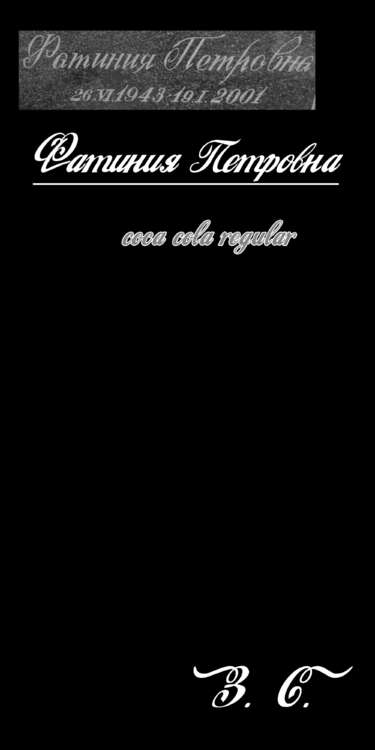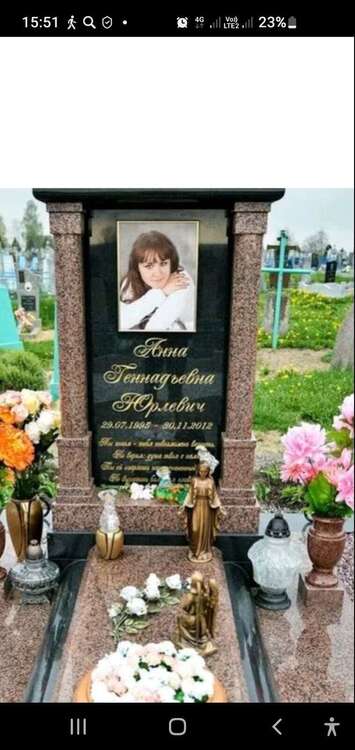
Помогите найти шрифт!
помогите найти шрифт!
@puzh с далека таймс прокатит. если не опытный заказчик. не придерется к закорючкам.
Здравствуйте! Помогите пожалуйста найти шрифт.
Что за шрифт? Вроде знакомый, а найти не получается. Даже распознаватели шрифтов не определяют. Бил, вроде как станок.
@AndreyV эпит тот же Italic
Здравствуйте! Может кто подсказать, пожалуйста, максимально схожий на этот ручной шрифт (имя, отчество, даты). Спасибо! )
максимально схожий
не совсем конечно максимально но что то есть рядом
подскажите, вроде был у меня раньше а какой не могу вспомнить и найти
Подскажите пожалуйста, что за шрифт?
Я понимаю что это ручная работа но может кто то знает похожие буквы
Подскажите что за зверь
Подскажите что за шрифт?
Пожалуйста срочно нужен шрифт.thumb.jpg.4740d7637f5ff64482adf91f86f47f20.jpg
olietta script bolditalic
Помогите найти шрифт...:excl::hi: